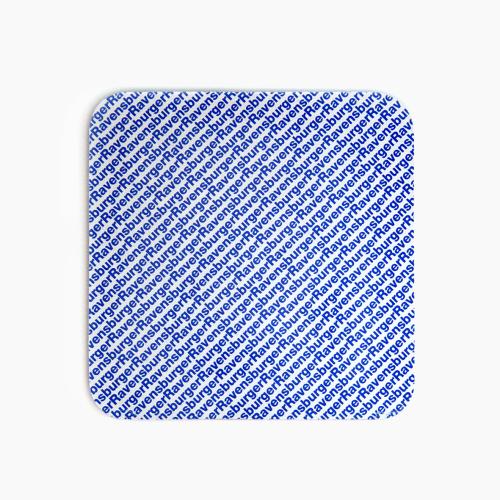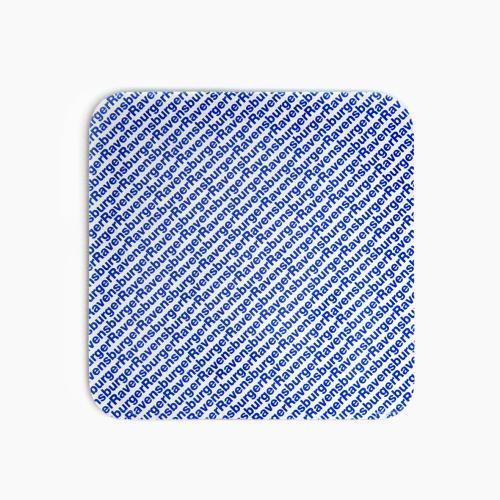
ravensburger schrift
ich suche die Schriftart, die auf der Rückseite der Ravensburger Memory-karten zu sehen ist.
Die aktuelle Hausschrift von Ravensburger ist "The Sans", dien Beispiel scheint aber älter und eine Helvetica zu sein.
Puh, schwer zu sagen. Könnte etwas in Richtung Helvetica Bold sein. Eine TheSans ist es jedoch nicht (siehe g, a, e). Vielleicht auf neueren Karten …
Nur mal eine Frage: Das kleine a auf der gezeigten Karte ist doch keine Helvetica, oder? Das sieht fast eher nach Arial aus …
Hast recht. Aber wenn man die Datei anschaut, die Ralf verlinkt hat, dann sieht das auch noch mal wieder andern aus.
Na, dann vielleicht auch was »Älteres«? Irgendwie ein »Gemisch« aus Helvetica und Akzidenz Grotesk? Dieses Helvetica-ähnliche Logo von Ravensburger ist ja auch schon ein paar Jahrzehnte alt – und vielleicht sogar irgendwie »gezeichnet« worden?!
… oder es ist einfach bloß eine Univers ...